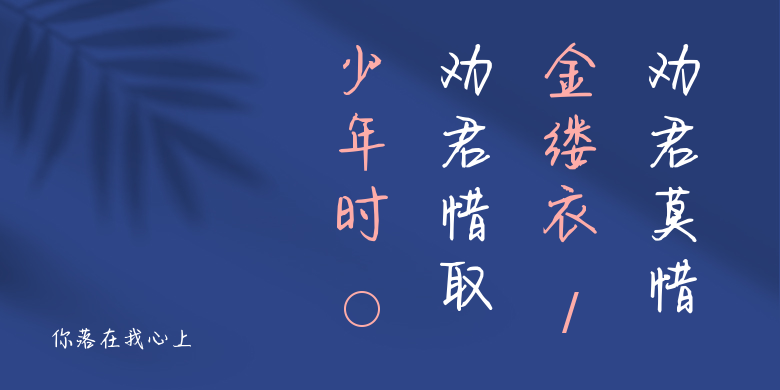
你落在我心上
你落在我心上,这款字体结构工整、笔画清晰,兼顾美观与易读性,适用于标题、正文、海报、包装、LOGO 等多种场景。字形优雅稳定,风格百搭耐看,适配日常排版与创意设计,让文字呈现更舒适、更具质感。你落在我心上一笔一画,皆是细节,以均衡的比例、流畅的线条打造舒适视觉体验,字形端正大气,风格简约现代。无论是商业设计、品牌宣传还是日常排版,都能轻松驾驭,让文字更有格调与力量。你落在我心上字体下载。